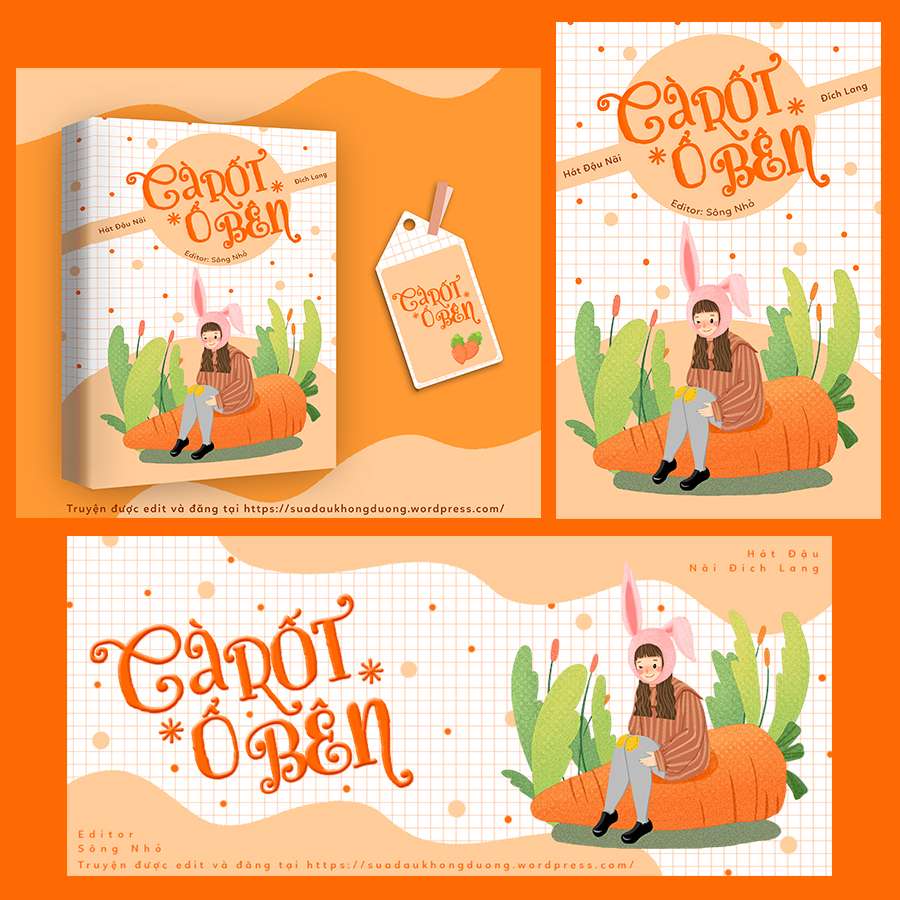
Font việt hóa MTD Bechamel Roman
Giới thiệu về Font việt hóa MTD Bechamel Roman
Trong thế giới đồ họa hiện đại, việc lựa chọn một Font Miễn Phí chất lượng đóng vai trò quyết định đến sự thành công của tác phẩm. Font việt hóa MTD Bechamel Roman là một lựa chọn hoàn hảo cho những ai đang tìm kiếm sự kết hợp giữa nét cổ điển và hơi thở đương đại. Bộ font này được chăm chút tỉ mỉ trong quá trình Việt hóa, giúp các nhà thiết kế tại Việt Nam dễ dàng sử dụng mà không lo lỗi dấu hay khoảng cách chữ không đều.
Đặc điểm nổi bật của Font việt hóa MTD Bechamel Roman
Thiết kế Serif tinh tế và sang trọng
MTD Bechamel Roman thuộc dòng chữ có chân (Serif) với đường nét thanh mảnh nhưng vô cùng dứt khoát. Cấu trúc chữ được xây dựng dựa trên tỷ lệ hình học chuẩn xác, mang lại cảm giác chuyên nghiệp và tin cậy. Khi sử dụng Font việt hóa MTD Bechamel Roman, các em học sinh và thầy cô có thể dùng để trình bày báo cáo, làm Slide bài giảng hoặc thiết kế thiệp mời trang trọng.
Khả năng ứng dụng đa dạng trong thực tế
Không chỉ dừng lại ở các văn bản hành chính, bộ font này còn tỏa sáng trong các dự án thương hiệu như logo, bao bì sản phẩm và bìa sách. Với bảng mã chuẩn Unicode, bạn có thể gõ tiếng Việt một cách mượt mà trên các phần mềm phổ biến như Photoshop, Illustrator hay Microsoft Word. Sự linh hoạt này giúp tiết kiệm thời gian chỉnh sửa thủ công cho người dùng.
Để phát huy tối đa vẻ đẹp của font chữ, bạn nên kết hợp nó với các màu sắc trung tính hoặc pastel nhẹ nhàng. Việc điều chỉnh khoảng cách dòng (leading) hợp lý sẽ giúp văn bản trở nên dễ đọc hơn trên màn hình máy tính và thiết bị di động. Hãy luôn kiểm tra kỹ bản in thử để đảm bảo mọi chi tiết hiển thị đúng ý đồ thiết kế.
Kết luận về bộ font chữ độc đáo này